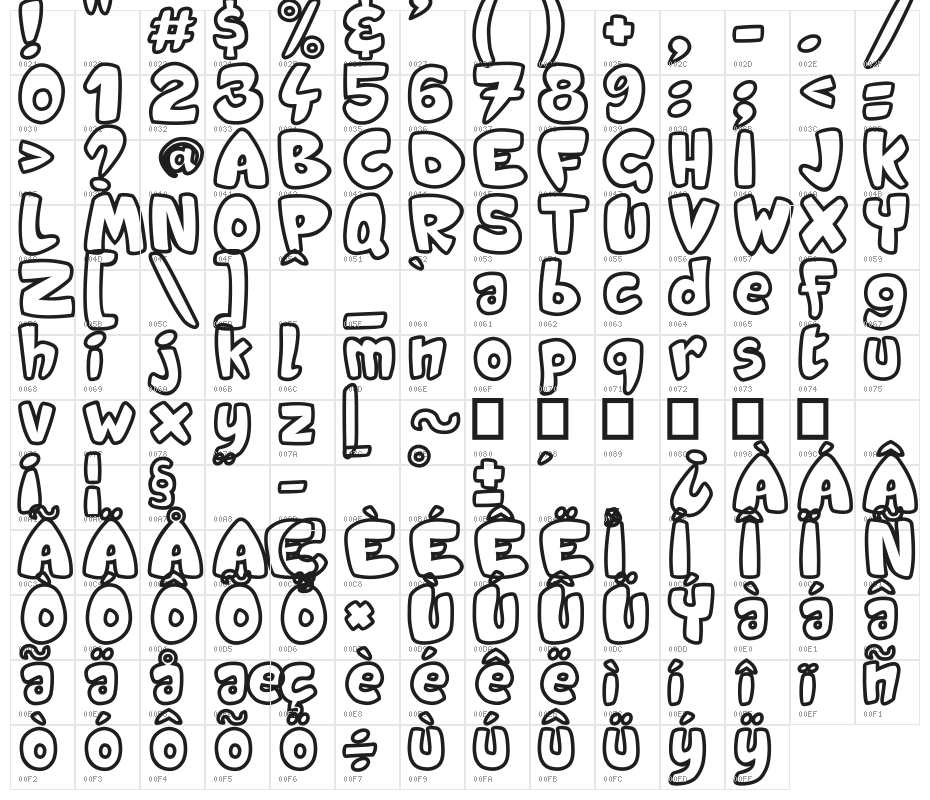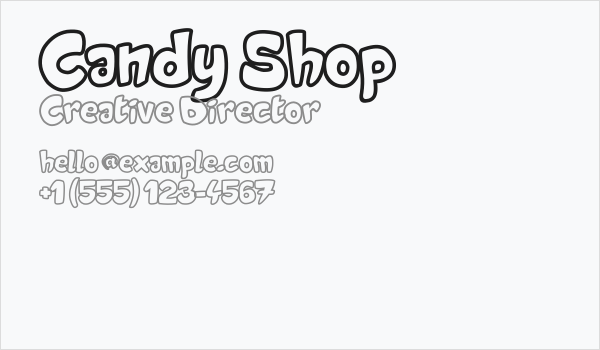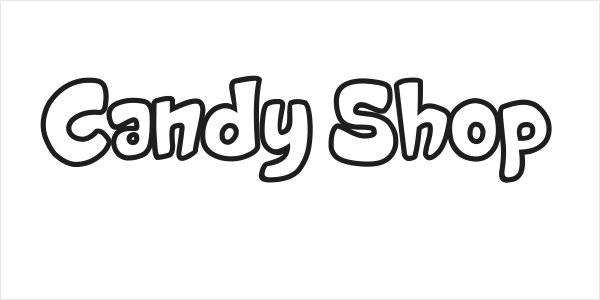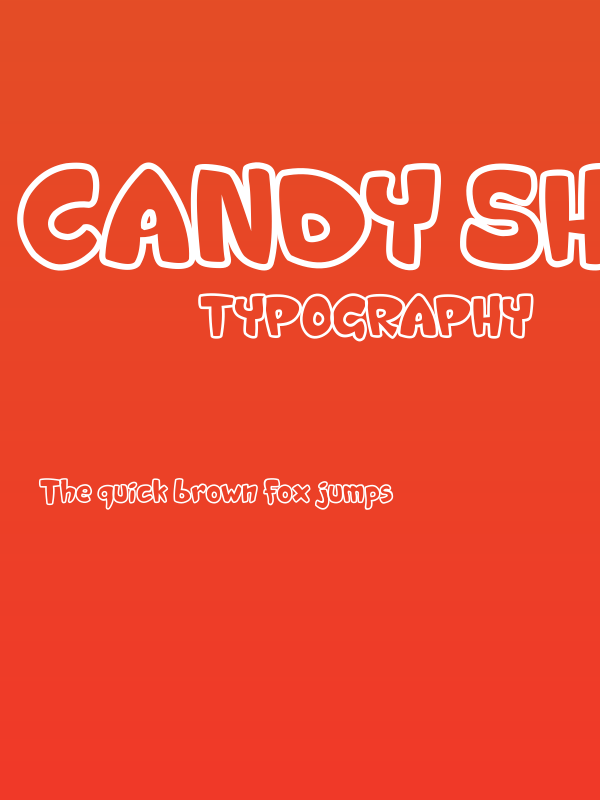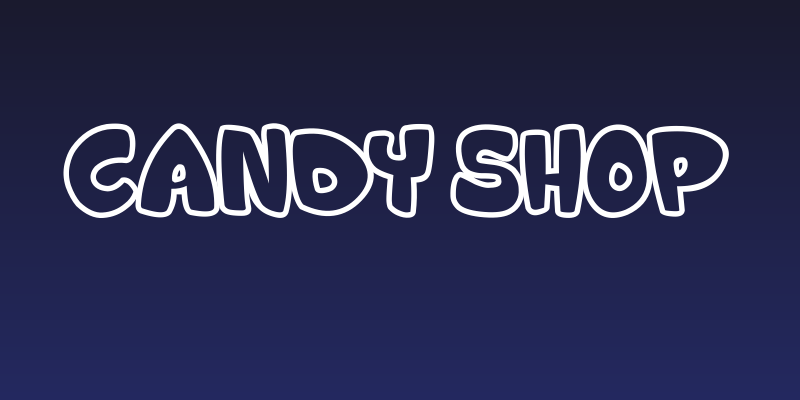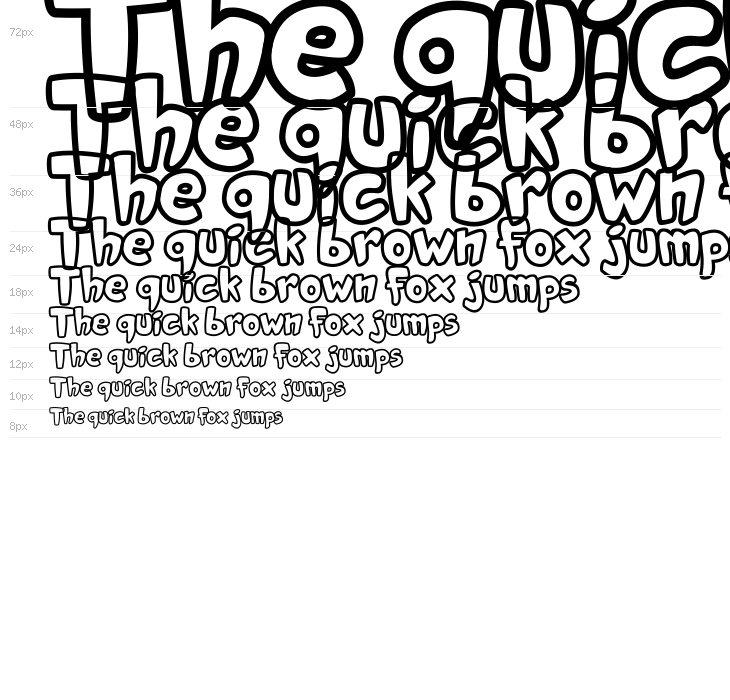
Candy Shop Font
| Gesamtstil | Playful, Cartoon-like |
| Vorgeschlagene Projekte | Ideal for children's book covers, playful branding, party invitations, and any project needing a fun, engaging typeface. |